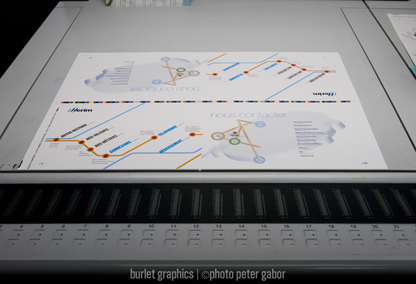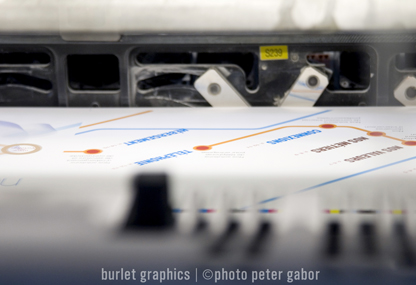
Analyse et décryptage d’une nouvelle identité graphique de Nerim, fournisseur de services Internet historique puisque cette société a été une des premières à proposer des connexions haut débit ADSL/SDSL dès 1999.
Nerim m’a confié la réflexion print et image de marque et à Jean-Charles Baudot, designer interactif, la mission de rebâtir son site web qui sera en ligne* dans les jours qui viennent.
Ce travail a demandé près de six mois de mise au point, d’aller-retours, d’un travail collaboratif sur un mode itératif afin d’en valider chaque étape et avancer avec une relative prudence.
Une création c’est souvent l’occasion de rencontres passionnantes.
C’est l’histoire d’une rencontre entre Jean-Charles Baudot et moi-même au sein des designers interactifs, celle d’un client qui était désireuse de reconstruire sa marque pour gagner en visibilité sur un marché de plus en plus tendu où tous les coups sont permis. Haut débit, bientôt la fibre optique, double play-triple play, les offres ne cessent de se multiplier et les opérateurs de se diversifier.
Même les opérateurs mobiles s’y mettent. Or Nerim ne se situe pas dans cette catégorie de fournisseur grand public qui nous sied à la plupart d’entre-nous. Son périmètre d’intervention ce sont les PME et TPE qui ne souffrent d’aucun aléa, d’aucune coupure de la sorte. Qui ont besoin de se sécuriser contre les attaques de tous genres (Firewall). Mais aussi des clients qui ont des sites multiples (franchises, délocalisations de sites de production ou de commercialisation) qui doivent échanger des données sécurisées entre elles sans être pollué par la grande toile.
Nerim comme une poignée d’autres fournisseurs de services très spécialisés, propose donc à ses vingt mille clients une palette de produits et services adaptées presque sur mesure à chaque cas de configuration-client. Il n’en reste pas moins qu’historiquement cette société est avant tout un fournisseur d’accès. D’où le choix d’un logo simplissime et minimaliste qui rappelle le cœur de métier de Nerim. Les deux points / double slash que forme le N de Nerim est là pour rappeler le métier de base.
Le remercier également de m’avoir fait confiance sans jamais contester certains choix graphiques et notamment lors de la conception de la plaquette qui tout en étant très technique se devait d’être aussi spectaculaire que pédagogique. L’utilisation des espaces blancs pour rythmer la lecture fait sens dans un univers de parole aussi hermétique que l’informatique de réseau.
J’ai très vite compris qu’il fallait profiter de la largeur de pages à l’italienne afin d’assoir l’horizontalité des flux de transferts de données, c’est donc très naturellement que je me suis orienté vers une conception graphique où le plan de métro londonien me servait de trame pour signifier les échanges mais aussi la dynamique et la complexité des nœuds de croisements entre réseaux privés et virtuels (PN et IP-VPN).
Le choix de l’imprimeur était également stratégique. Burlet Graphics à Maisons Alfort , est coutumier des impressions délicates. Il s’agissait d’imprimer cette plaquette 24 pages sur un papier couché de 170g avec une couverture quadri recto verso et vernis brillant sélectif sur la Une. Le choix de l’Acrylique s’imposait. (Format Machine: 52 x 74cm).
L’imprimerie existe depuis fort longtemps, mais il s’est adapté à toutes les technologies modernes, calage électronique, CTP (plaques offset directement écrit au laser à partir de fichiers PDF certifiés que je lui déposais sur son serveur FTP). L’encrage comme vous allez le découvrir sur les images ci-dessous et surtout sur l’animation qui se trouve à la fin du billet, est entièrement piloté par l’informatique de production.
Point besoin désormais d’ouvrir des robinets d’encriers à la main pour faire monter le cyan ou la magenta sur telle ou telle zone du papier. C’est sous un éclairage équilibré à 5200°K, lumière du jour que l’on regarde et mesure au densitomètre la puissance des couleurs et que l’on «monte» ou «baisse» le débit de l’encrage. Les réglages sont automatiquement mémorisés de sorte que vous pouvez ré-imprimer six mois après, les données de l’impression seront stockées en mémoire. Juste aussi pour signaler qu’il s’agit là d’un des rares imprimeurs ayant obtenu en France le label vert d’imprimerie «durable», ne rejetant plus aucun déchet non-recyclable et dangereux pour l’environnement.
Cette animation vous montre très précisément comment se déplacent les réservoirs d’encre pour «distribuer» celle-ci le long des rouleaux encreurs.